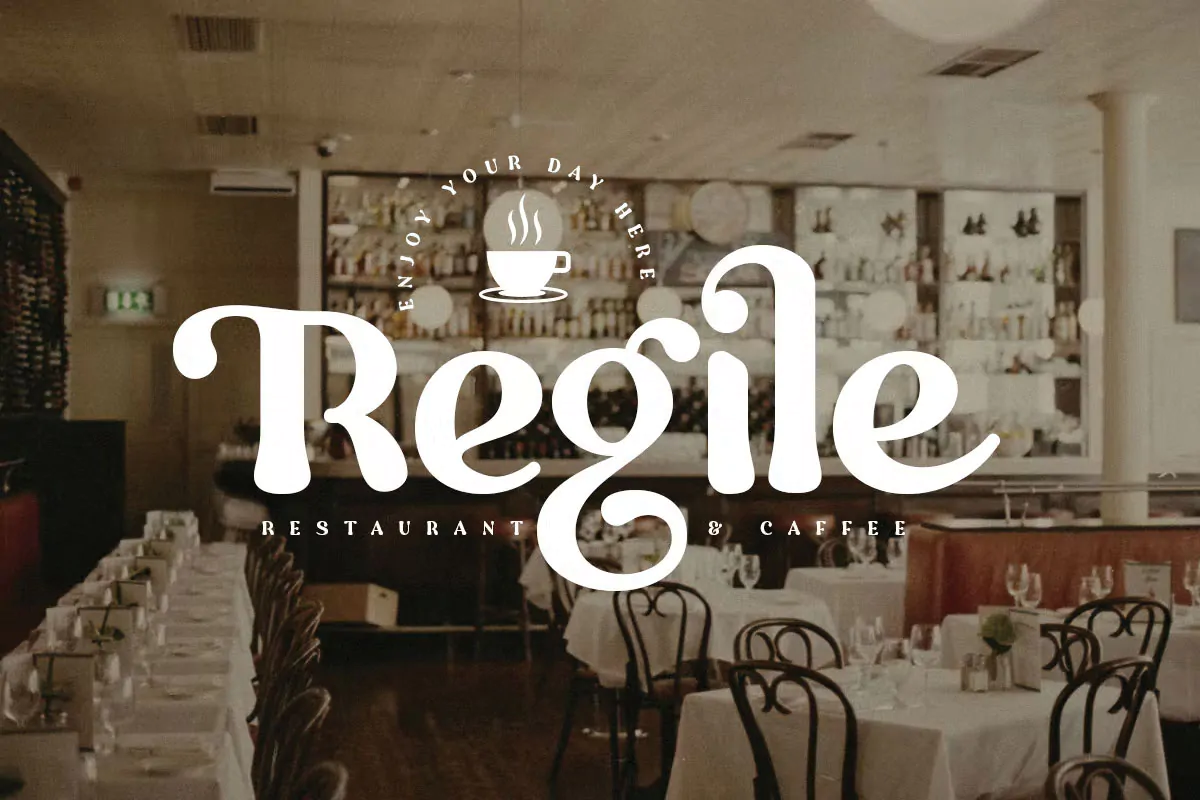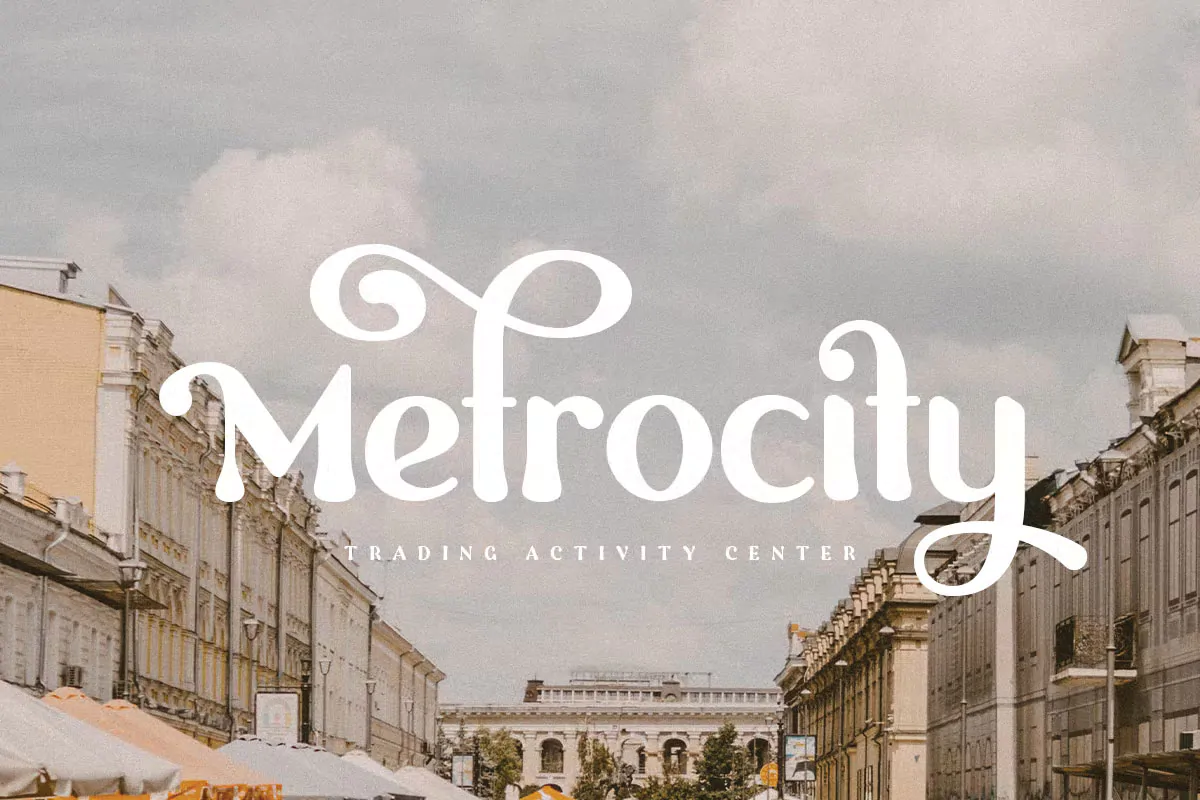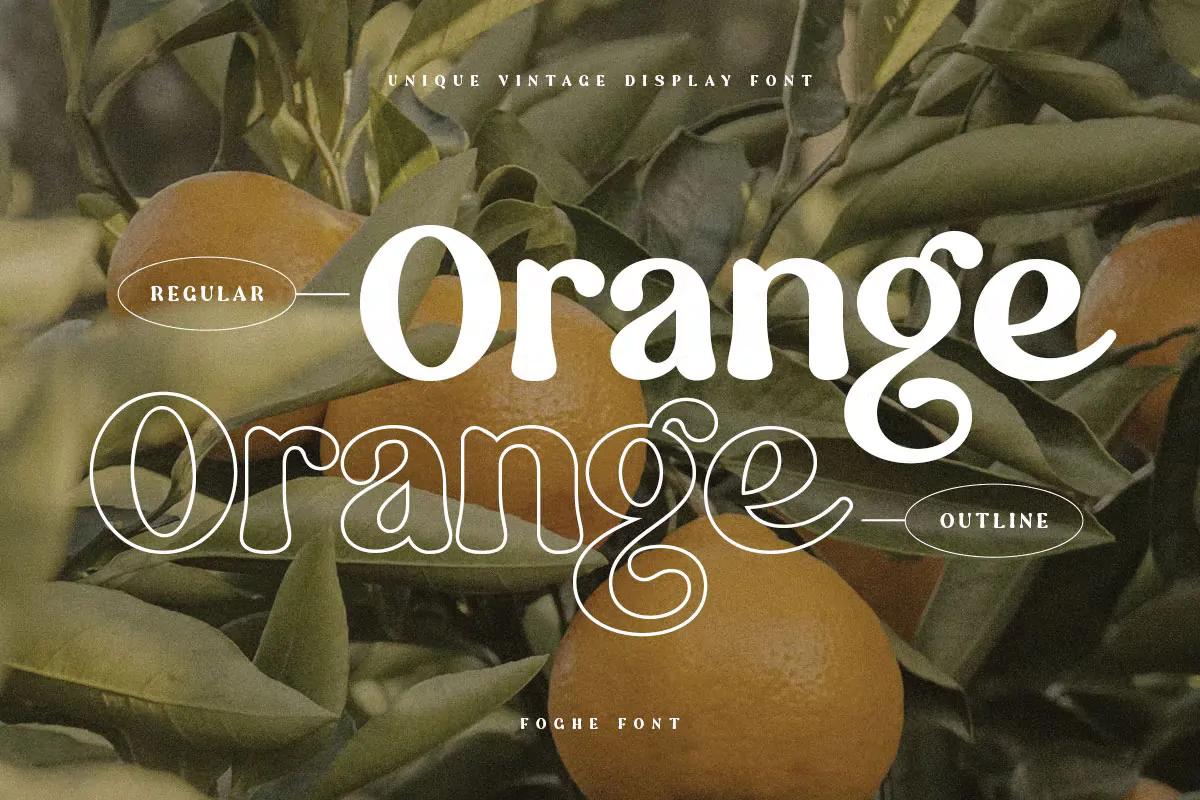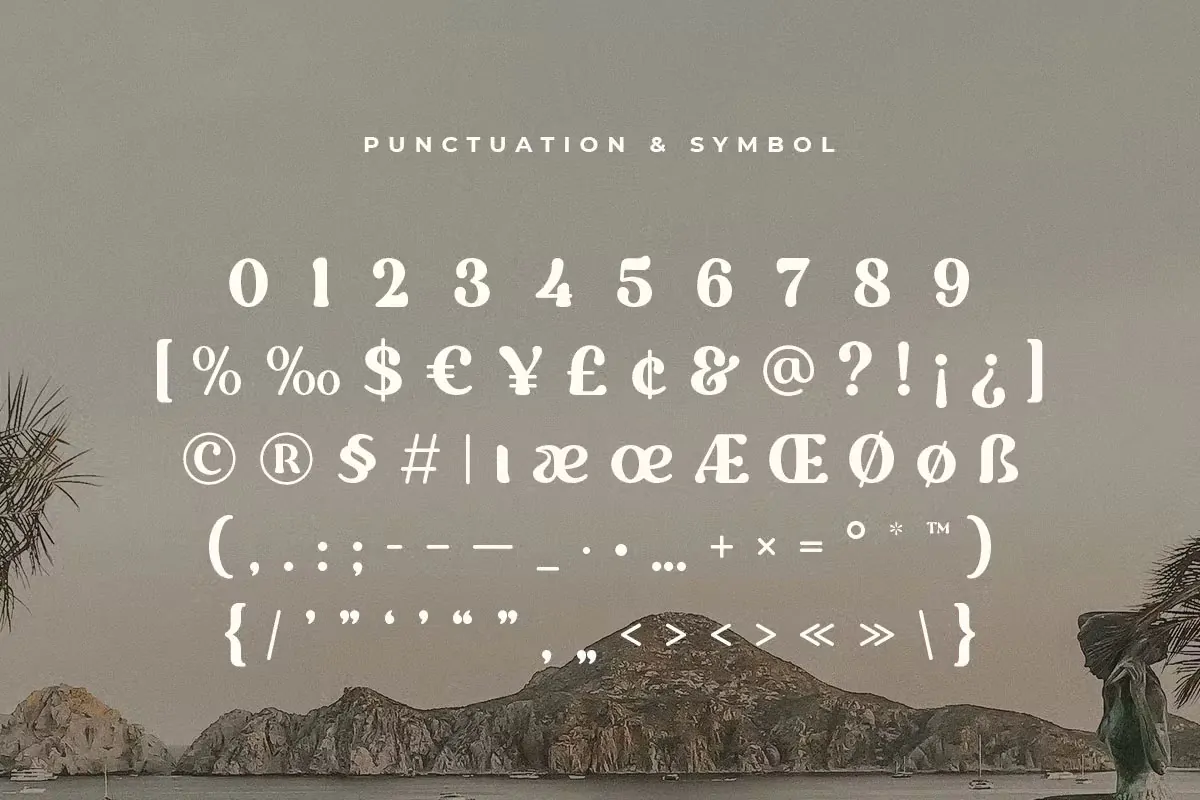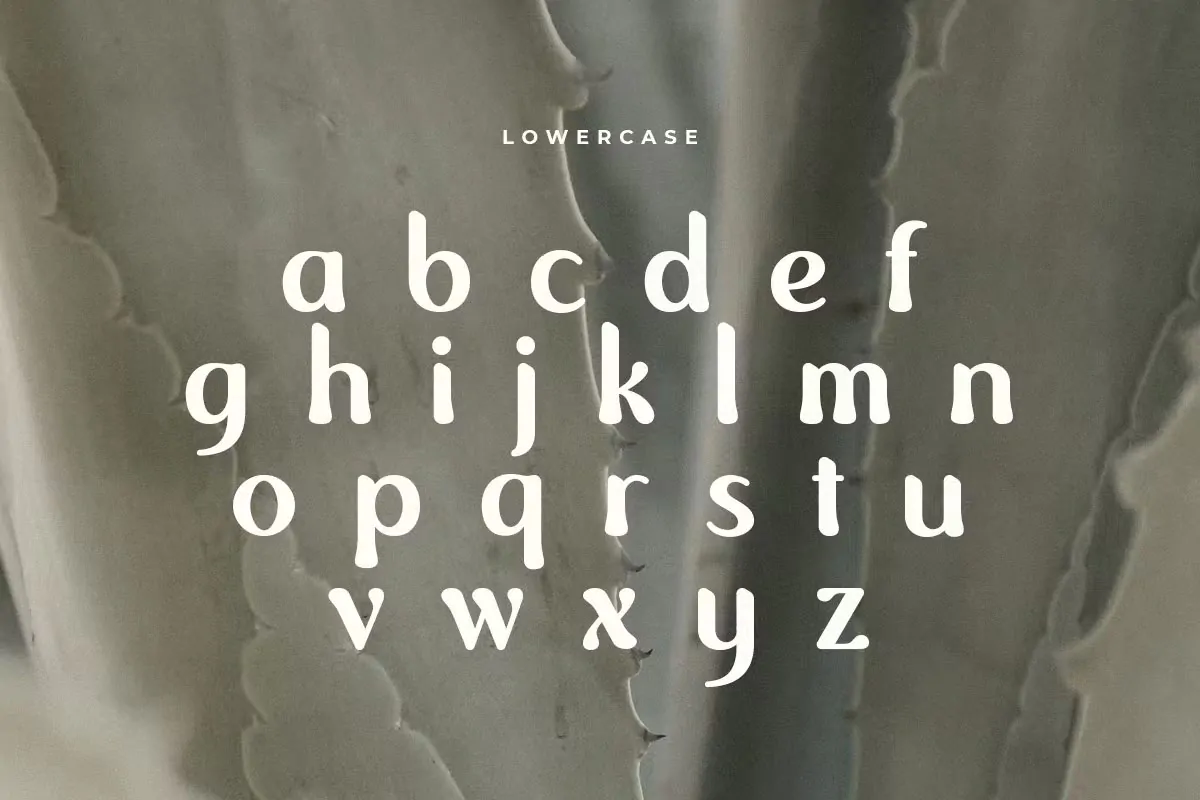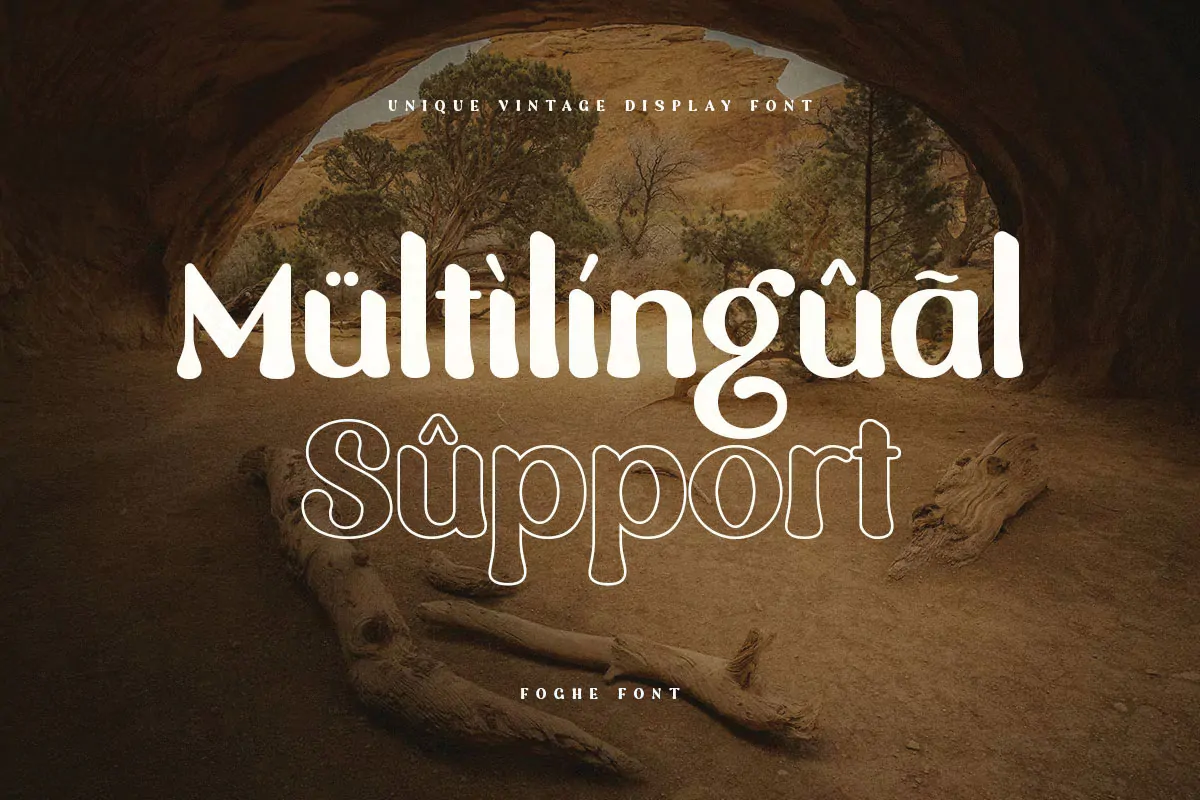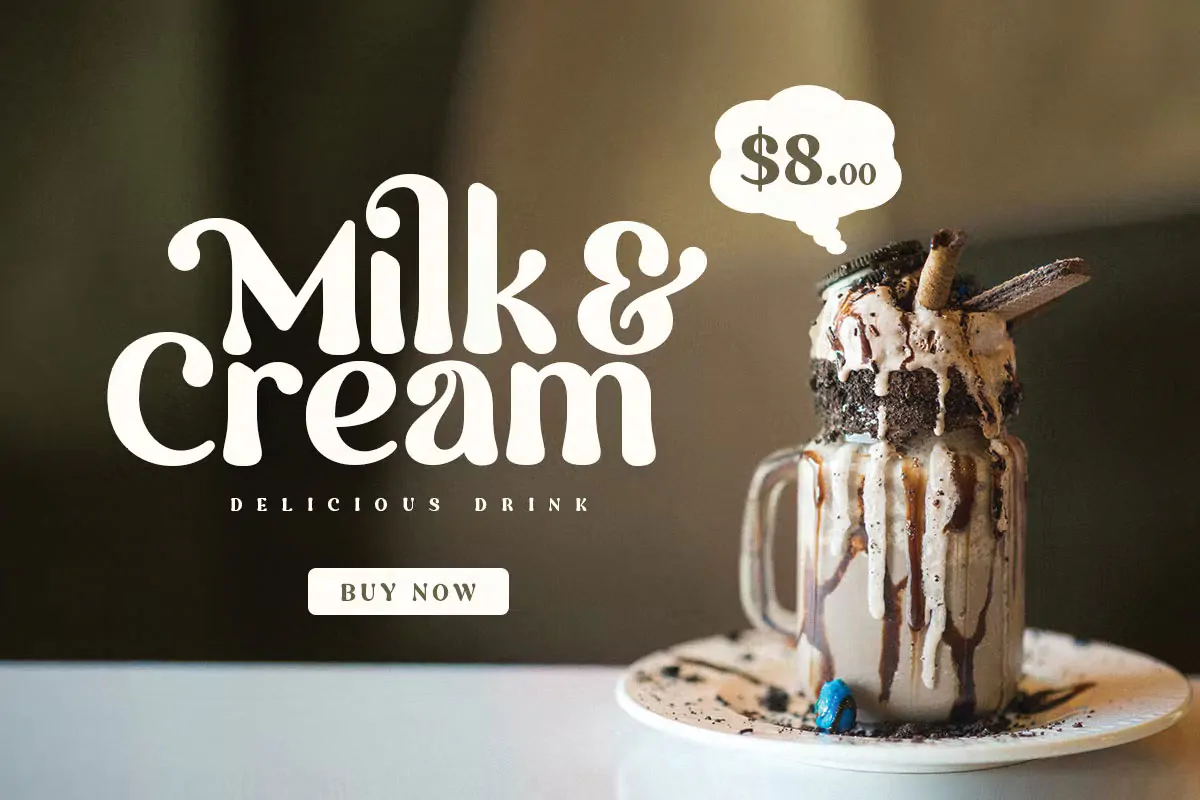
فونت کلاسیک Foghe
فونت کلاسیک انگلیسی
فونت کلاسیک Foghe یک قلم نمایشی وینتج انگلیسی است که مناسب برای استفاده در طرحهای مختلف همچون طراحی انواع پوستر، جلد کاور آلبوم موسیقی، مجلات، چاپ تیشرت، بسته بندی محصولات، ظروف یکبار مصرف، لوازم التحریر و … میباشد.
- Regular، Outline